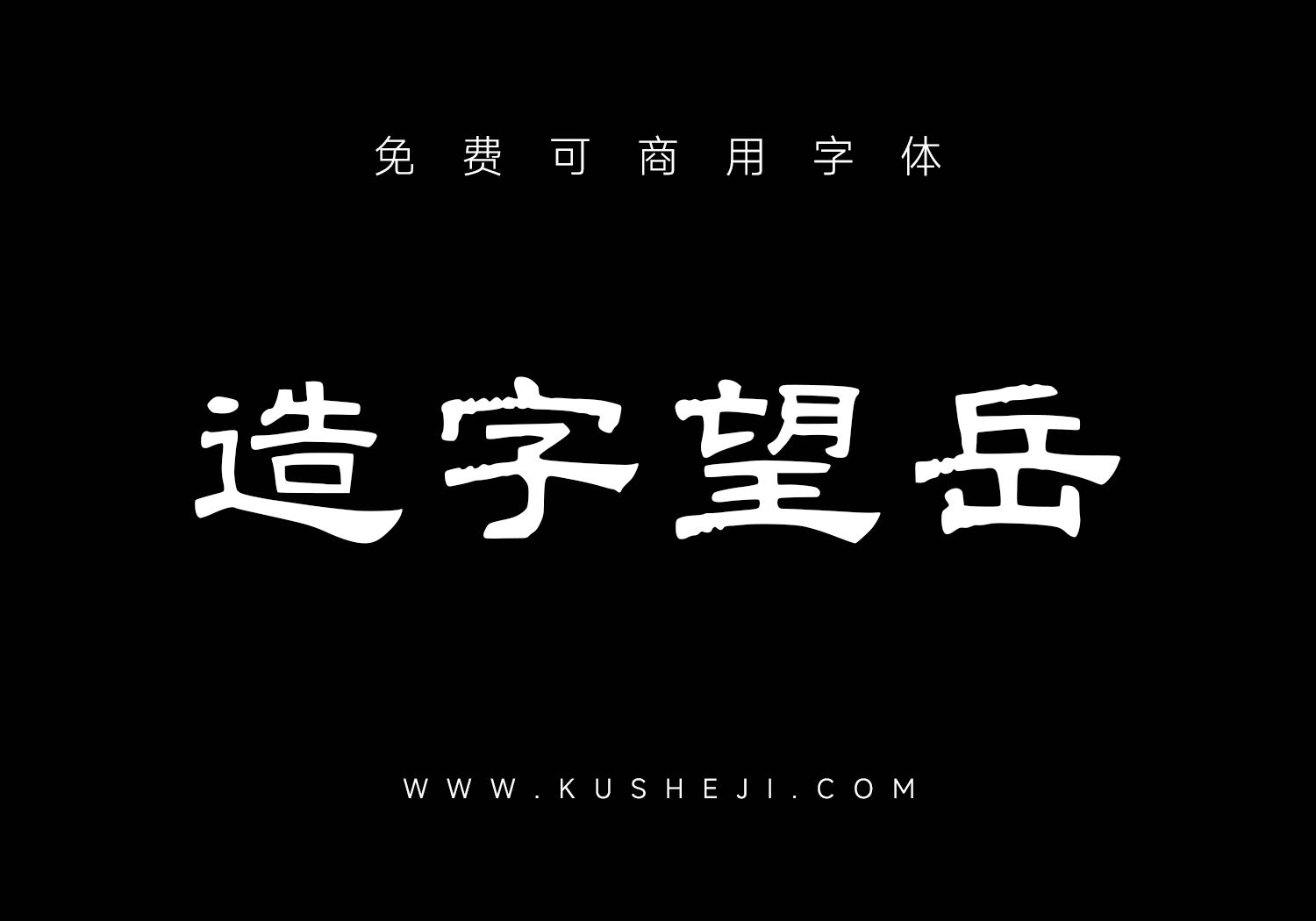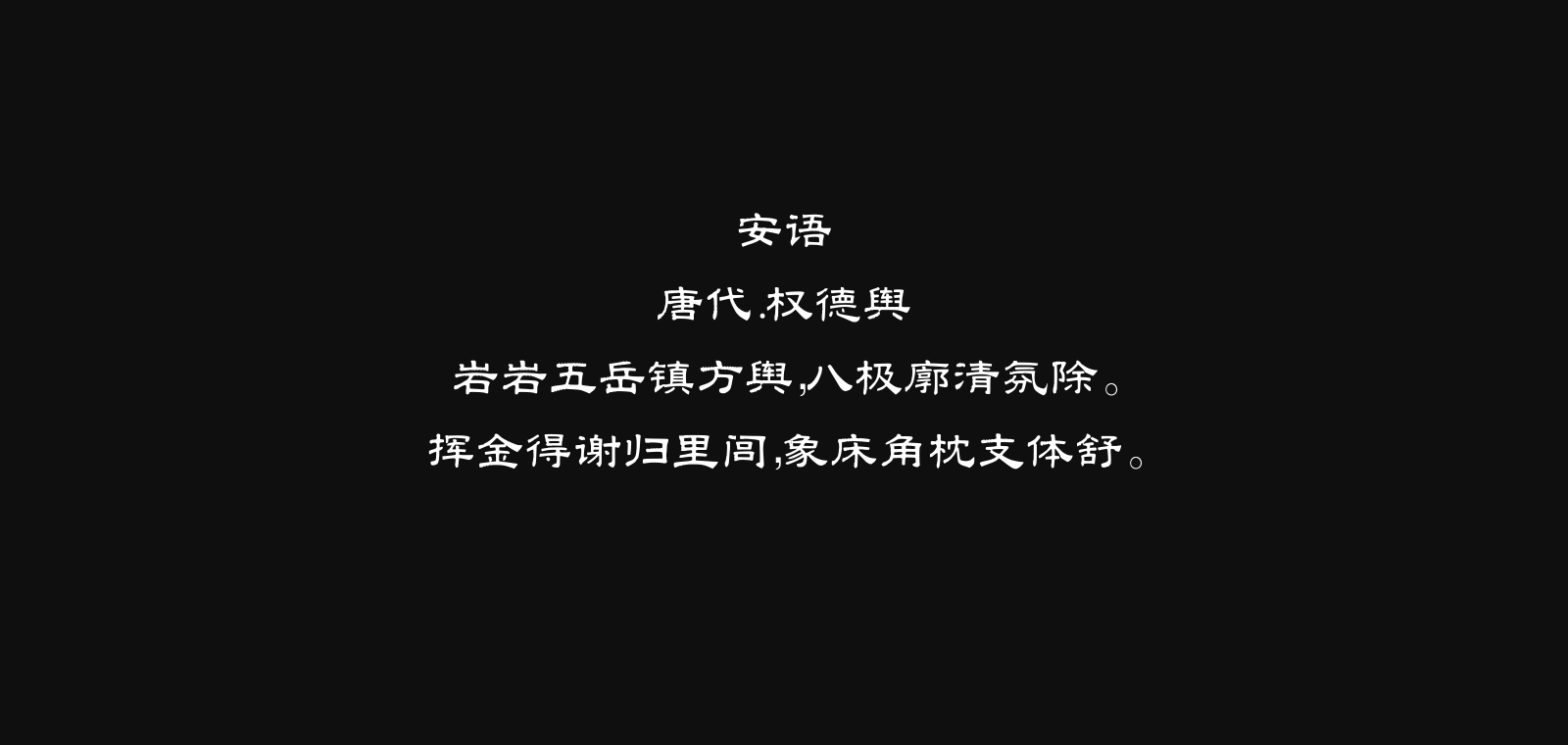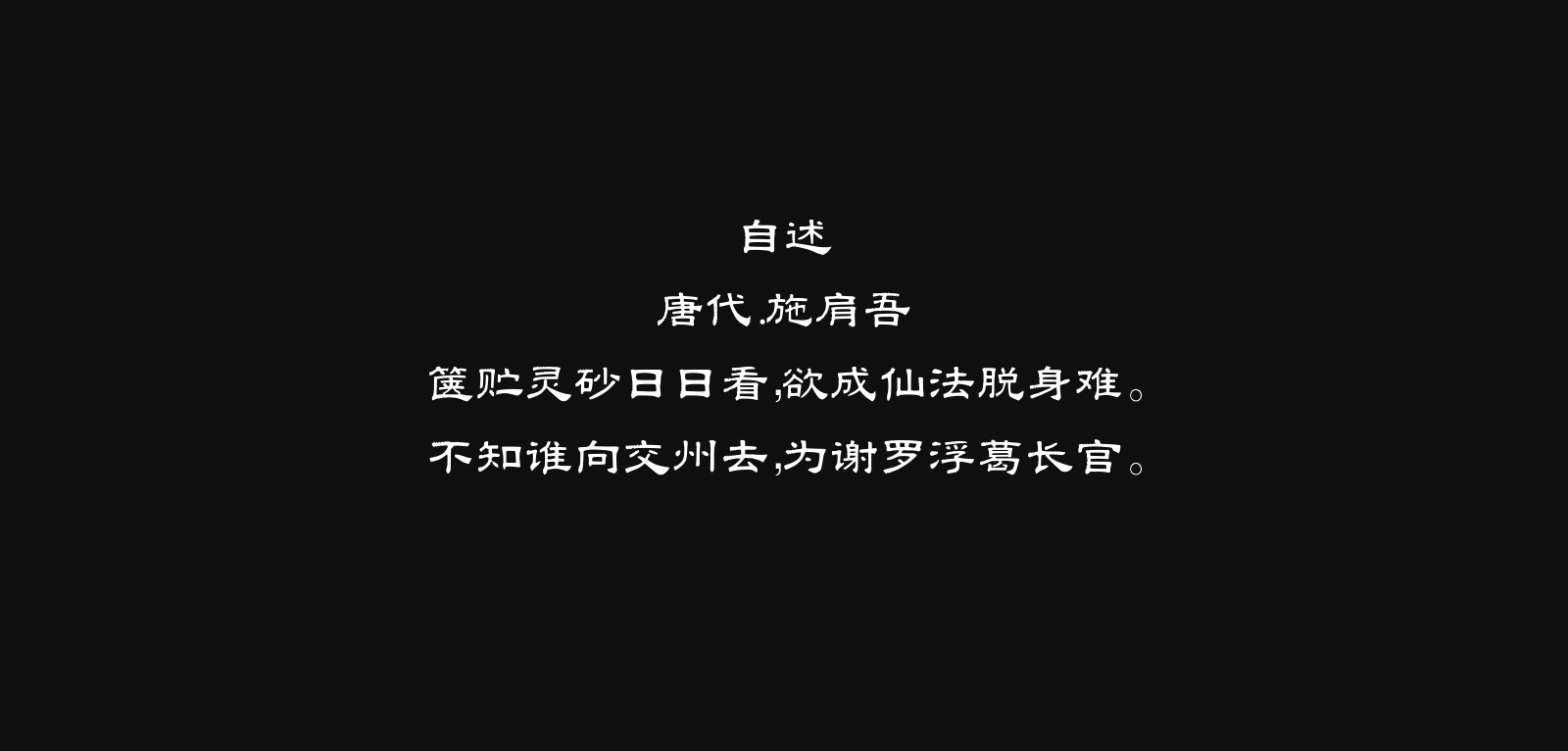
字体家AI造字望岳是一款由字体家AI神笔造字生成的一款艺术字体,此字体横画起笔略顿,收笔利落如切刀,竖画挺拔似柱,粗细均匀中藏筋骨。转折处方硬见棱角,又带微圆过渡,不生硬。结构重心沉稳,笔画边缘干净,兼具黑体的规整与手写的力道,像稳健的山石,端庄中透着坚实,给人可靠、大气、有分量的美感。适合用于广告、海报设计,平面设计等。